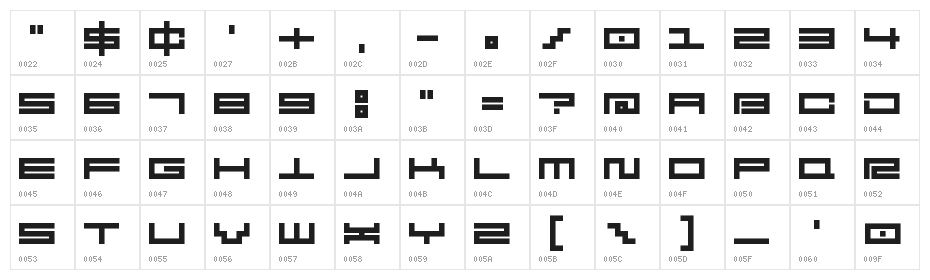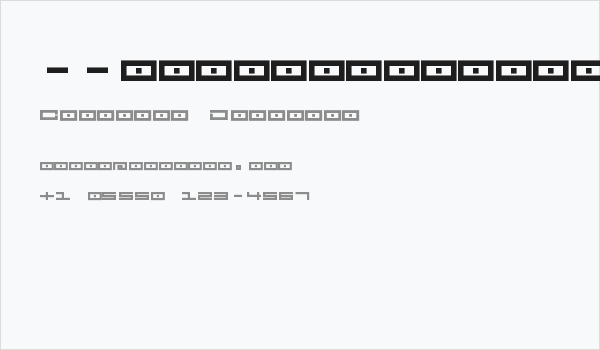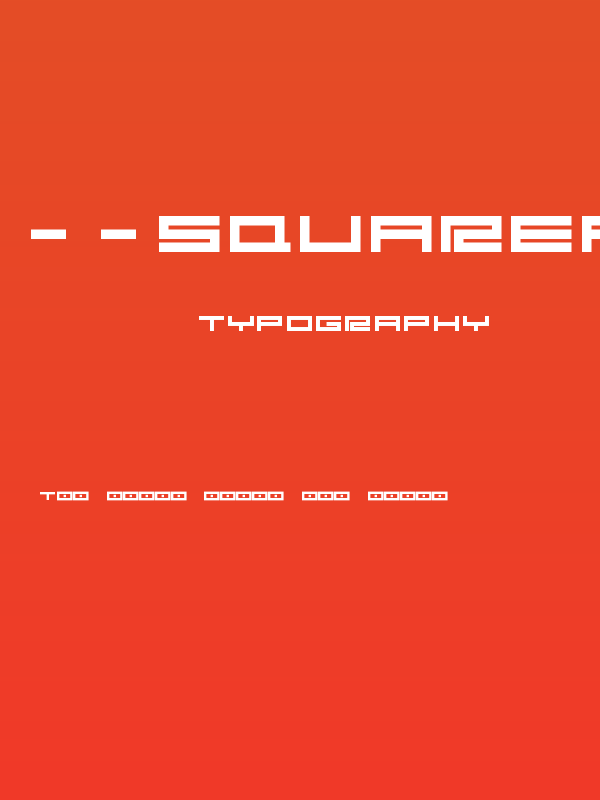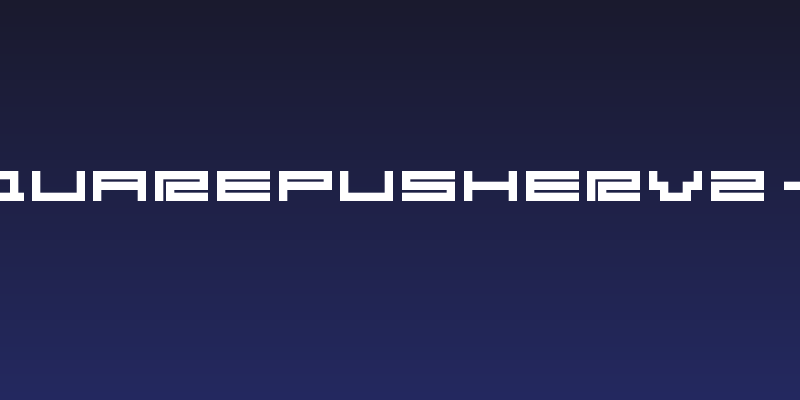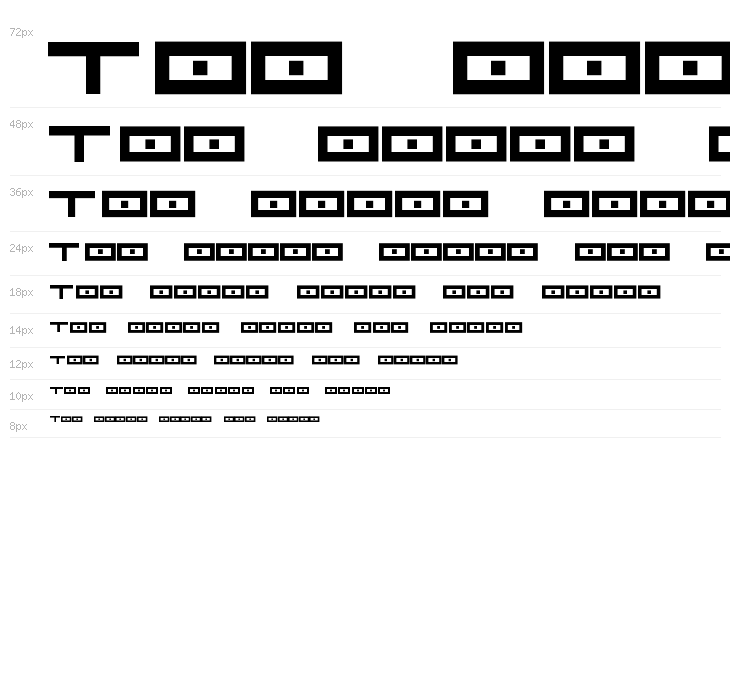
--squarepusherv2-5-- Font
| Progetti proposti | Ideal for tech-related branding, video game graphics, digital art projects, and retro-themed designs. |